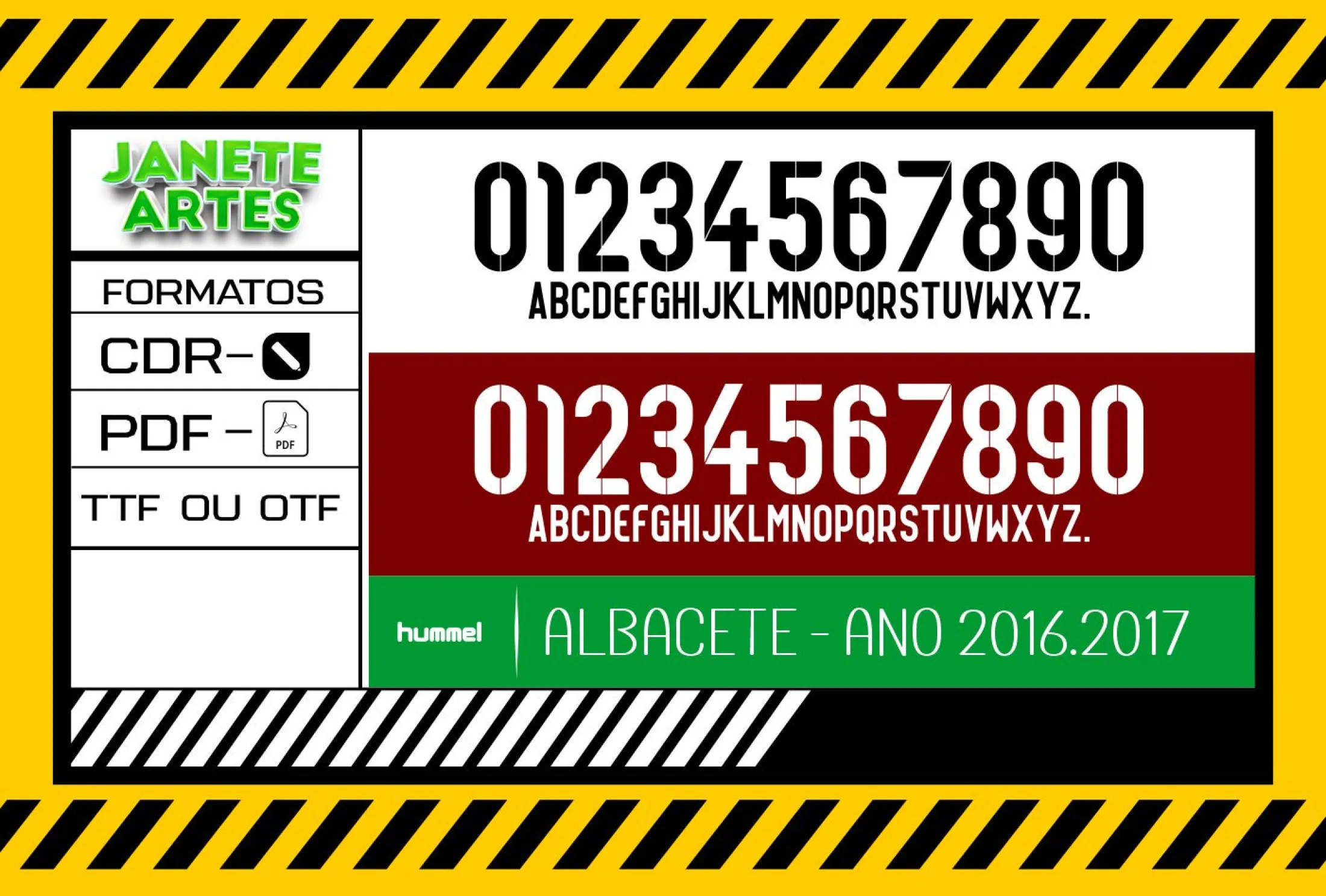
Fonte de Time Tipografia Albacete 2016 - 2017
• ✅ Alfabeto completo: letras A a Z e números 0 a 9
Arquivo Fonte de Time Tipografia Albacete 2016 - 2017 para camisetas, perfeito para personalizar camisetas com design exclusivo e tipografia estilizada de time para seus projetos criativos.
Uma História Inspiradora com a Fonte de Time Tipografia Albacete 2016 - 2017
• Tipografia personalizada inspirada no time Albacete, temporada 2016 - 2017.
Dicas e Ideias para Usar o Arte Fonte de Time Tipografia Albacete 2016 2017 para Camisetas